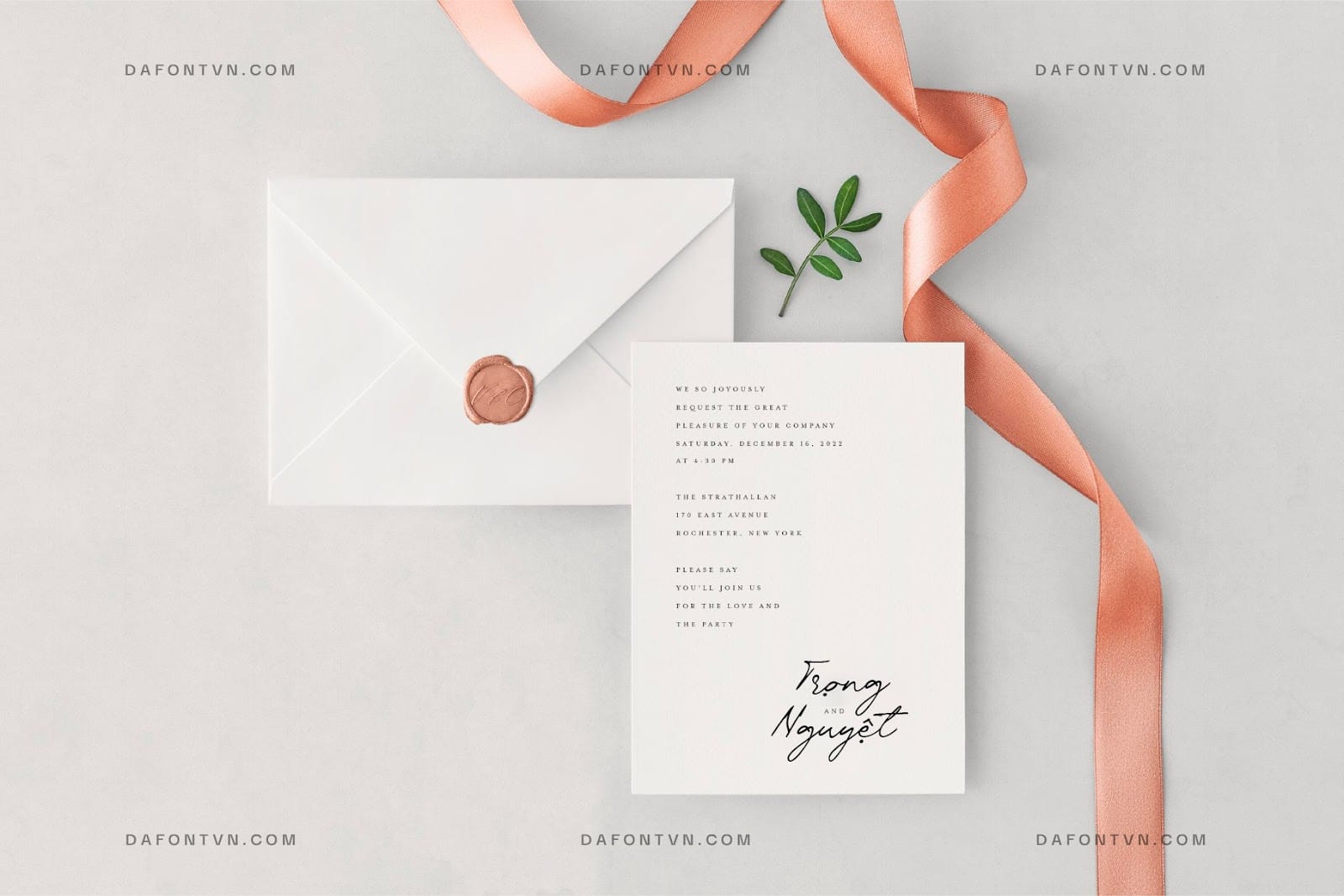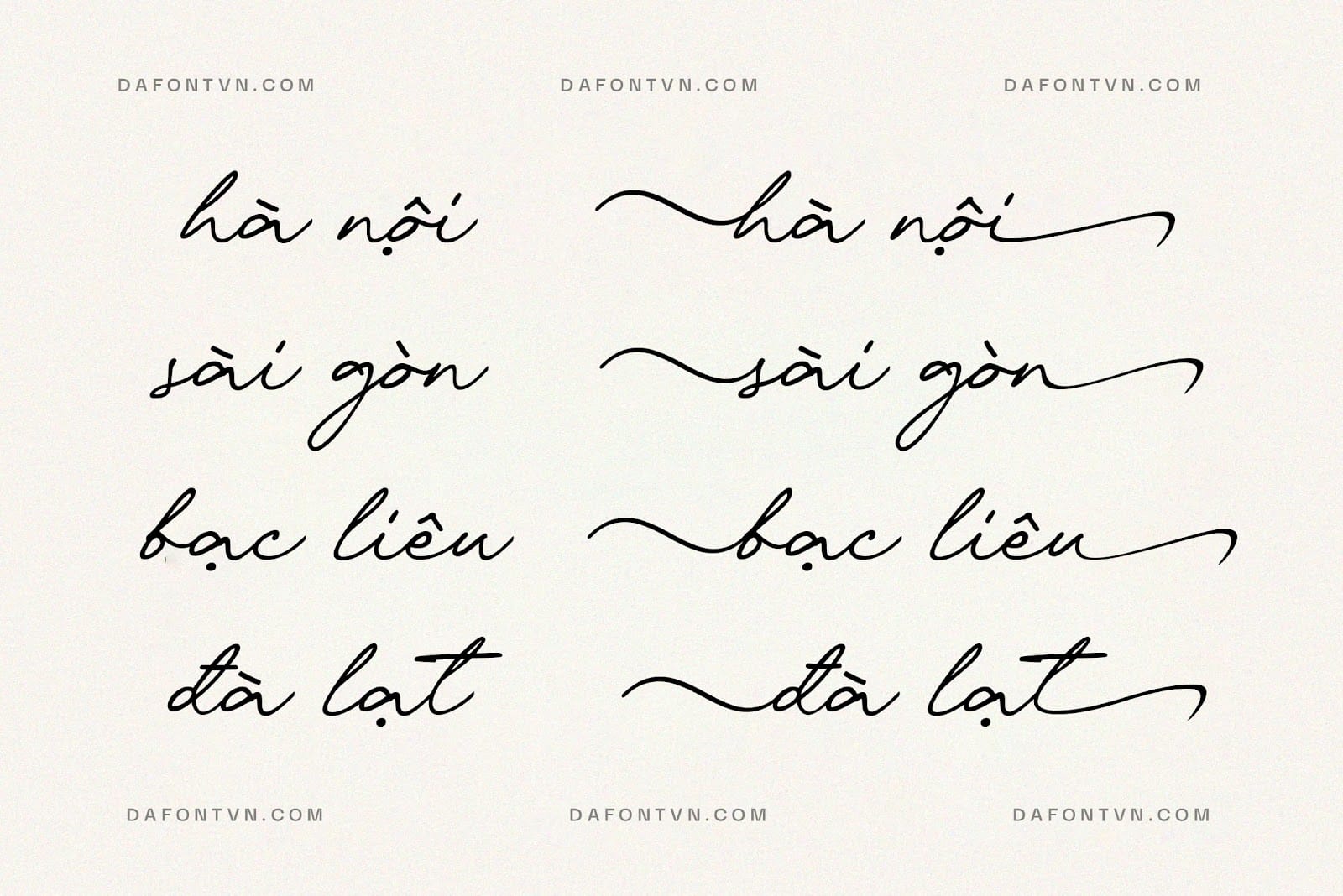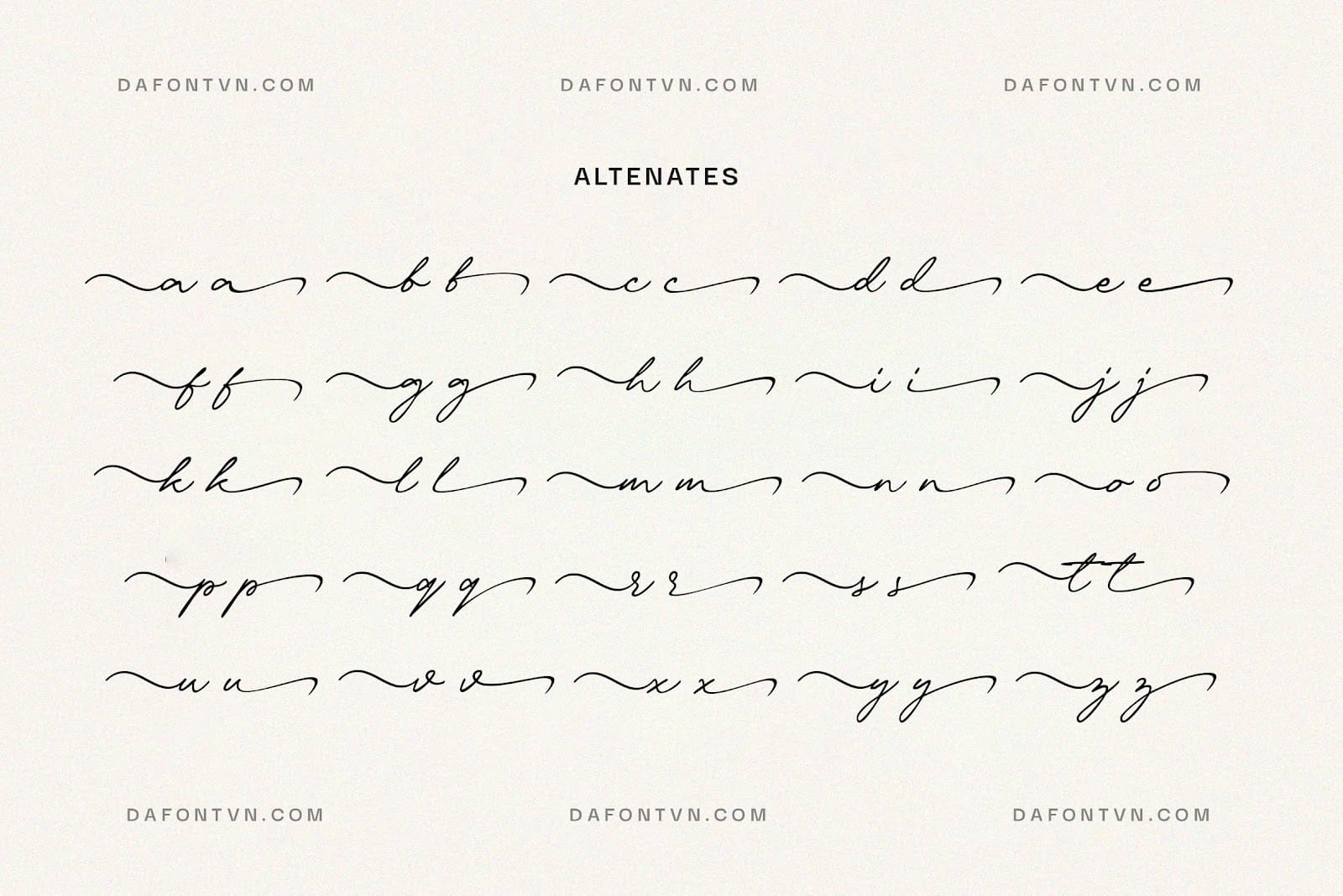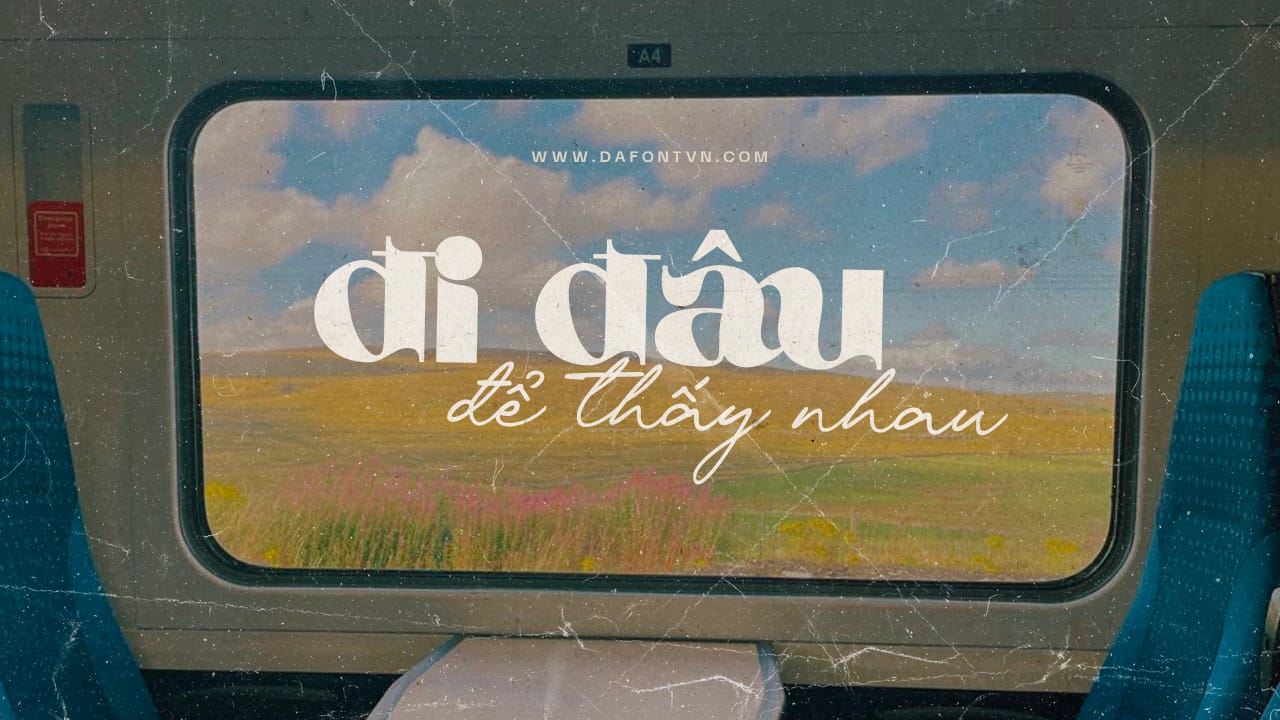
Whitegone là một font chữ viết tay ấn tượng được thiết kế mang lại cảm giác tự nhiên. Thiết kế độc đáo và cách điệu tinh tế của nó, tạo ra sự pha trộn hài hòa giữa các yếu tố truyền thống và đương đại.
Hoàn hảo cho nhiều dự án thiết kế khác nhau. Tính dễ đọc và tính thẩm mỹ của nó làm cho Whitegone trở thành một lựa chọn linh hoạt cho bất kỳ dự án thiết kế nào. Tóm lại, font Whitegone là một lựa chọn đáng chú ý cho các nhà thiết kế đang tìm kiếm một phông chữ viết tay, thanh lịch có thể thêm cá tính và sự quyến rũ cho thiết kế của họ.
Ngoài ra font chữ đi kèm rất nhiều glyph (có thể xem ảnh demo bên dưới) với các ký tự thường để bạn có thể sáng tạo cho ra nhiều các tác phẩm thiết kế ấn tượng hơn.